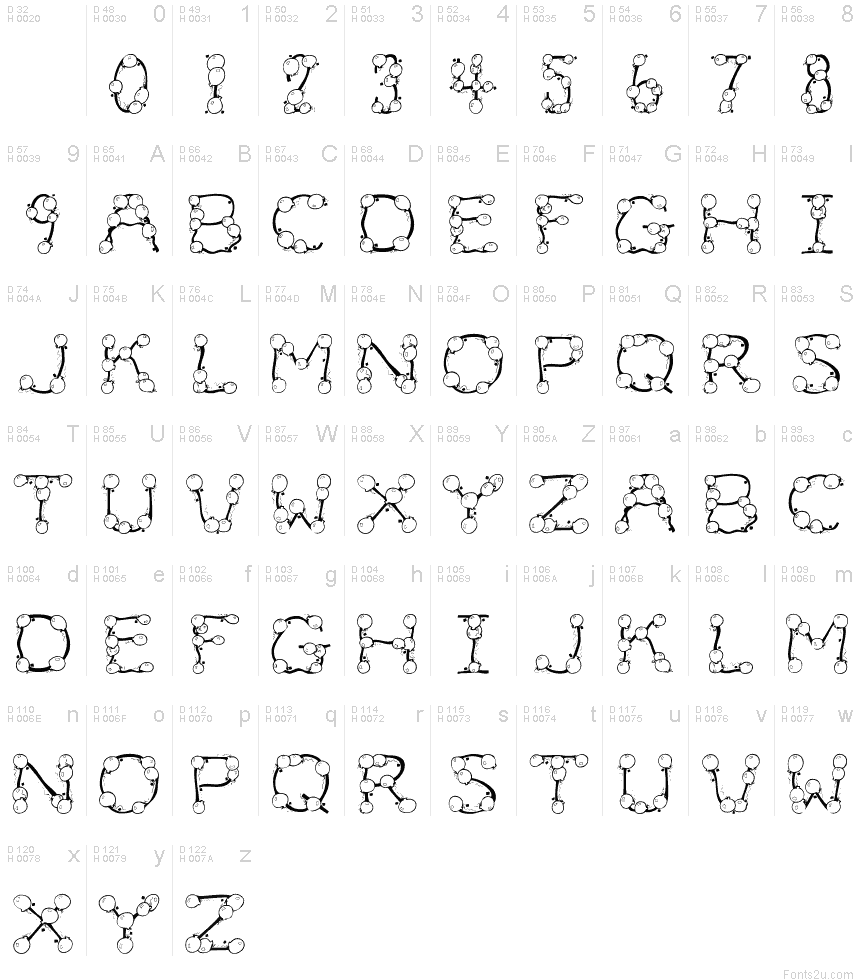
101! BalloonZ, zaprojektowany przez Nght, to darmowy krój pisma typu display w stylu kreskówkowym, zbudowany z grup nadmuchanych, ręcznie rysowanych kształtów o swobodnej kresce komiksowej. Każda litera wygląda, jakby była złożona z zachodzących na siebie balonów, z nieregularnymi konturami, małymi zawiązanymi końcami, błądzącymi kropkami i drobnymi refleksami świetlnymi, tworząc żywą sylwetkę, która sprawia wrażenie bardziej ilustrowanej niż złożonej z czcionek.
Sklep z artykułami imprezowymi lub marka dziecięca mogłyby wykorzystać te napisy do opakowań, plakatów wydarzeń, gadżetów i zabawnych szyldów, zwłaszcza w przypadku produktów skupionych wokół świętowania i zabawy, ponieważ balonowa konstrukcja zamienia każde słowo w osobną grafikę. Idealnie wpisuje się w dziecięcą rozrywkę o tematyce urodzinowej, cyrkowej i karnawałowej.